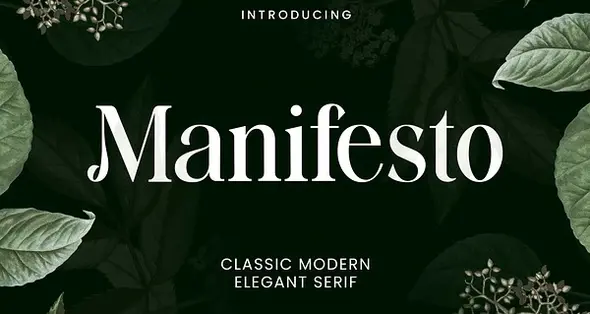
• فونت انگلیسی سریف مدرن کلاسیک
• Manifesto Classic Modern Serif Font
فونت انگلیسی سریف مدرن کلاسیک
• circle سایز پیشنهادی: فشن، ژورنال، مجله
• circle سبک قلم: Serif
• circle لیگچر
Manifesto یک فونت سریف کلاسیک و مدرن است که حس زیبایی، اصالت و استایل سطح بالا را به بیننده القا می‌کند. این تایپ‌فیس به شکلی طراحی شده که برای طیف وسیعی از پروژه‌ها، از امضاهای گرافیکی و ست اداری گرفته تا لوگو، طراحی عروسی، نقل‌قول‌های تایپوگرافی، جلد مجلات و کتاب، و سربرگ وب‌سایت‌ها ایده‌آل باشد.
این فونت در پروژه‌های برندینگ حوزه مد یا طراحی‌های تحریریه، به خوبی می‌تواند هر دو ویژگی ظرافت و قدرت را به نمایش بگذارد.
• مجموعه غنی از گلیف‌ها: شامل تعداد زیادی نویسه و فرم‌های جایگزین برای طراحی خلاقانه‌تر
Manifesto Classic Modern Serif Font. The modern display font feels beautiful classy, elegant, and stylish. This font is ideally suited for a wide variety of projects, such as signature, stationery, logo, wedding, typography quotes, magazine or book covers, website headers, branding, and more. Also, fashion-related branding or editorial design displays both masculine and feminine qualities.
- Ton of glyphs